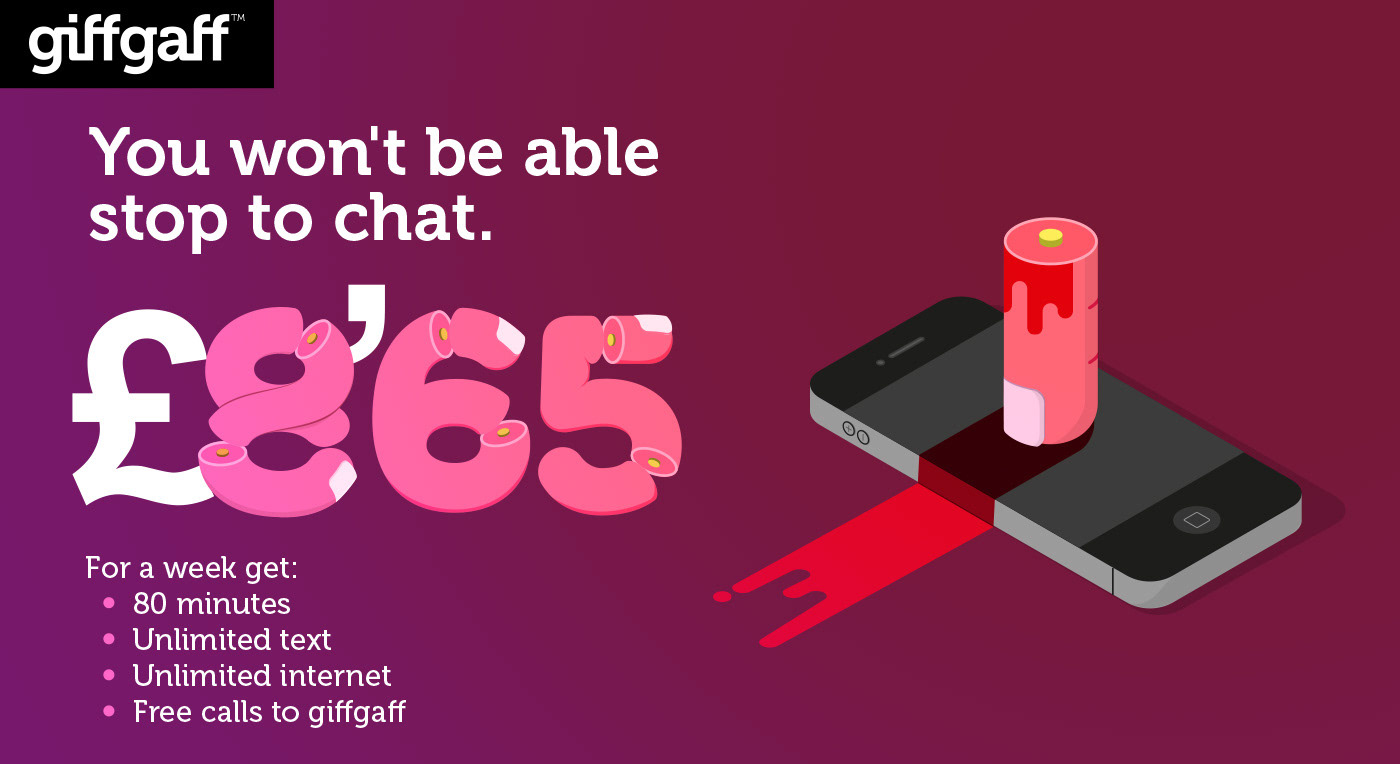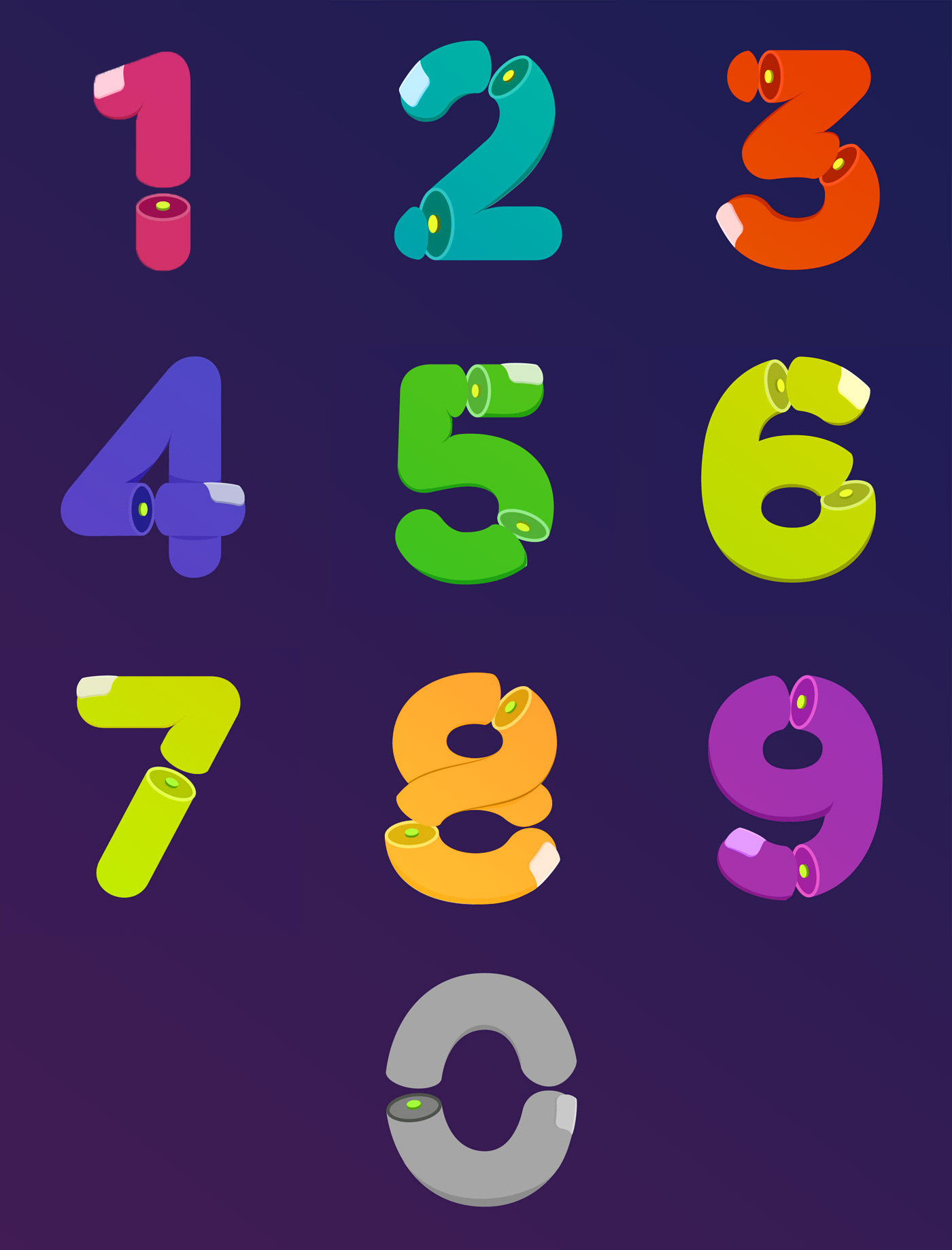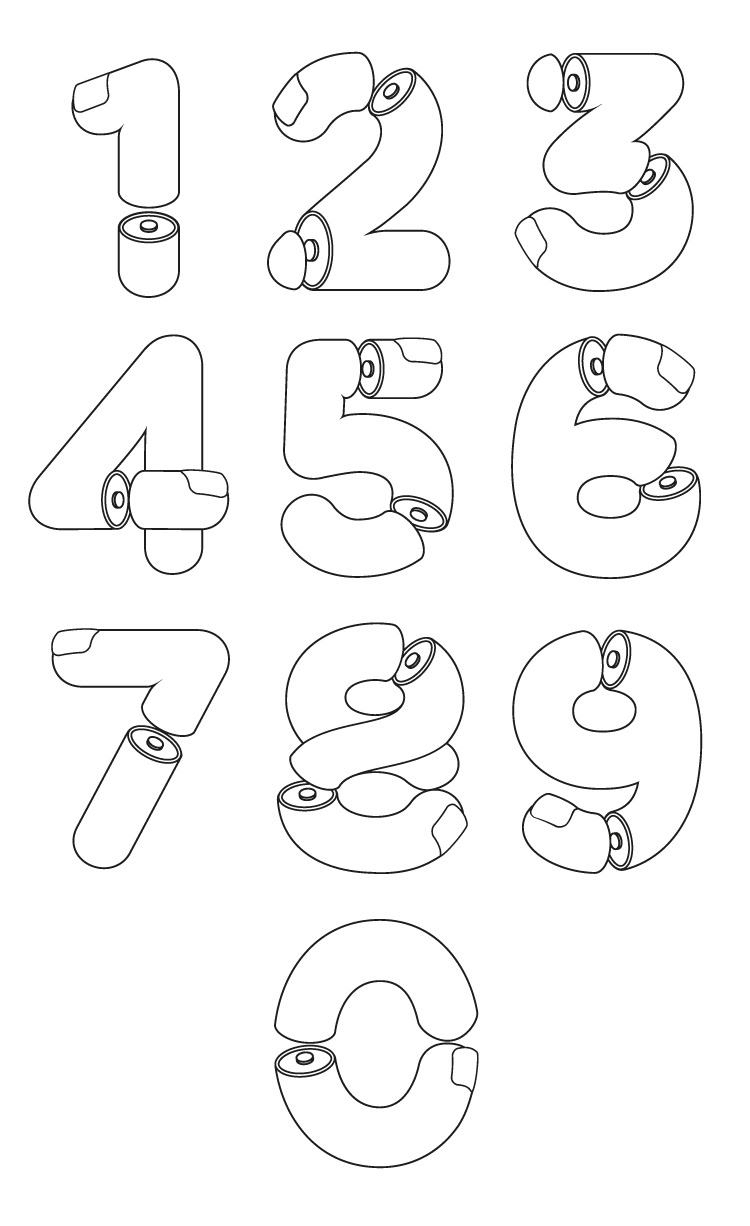
Numerología - Tactil cut
Una familia de números divertidos, con personalidad y algo sanguinolentos para apoyar una campaña ácida con un peculiar humor negro.